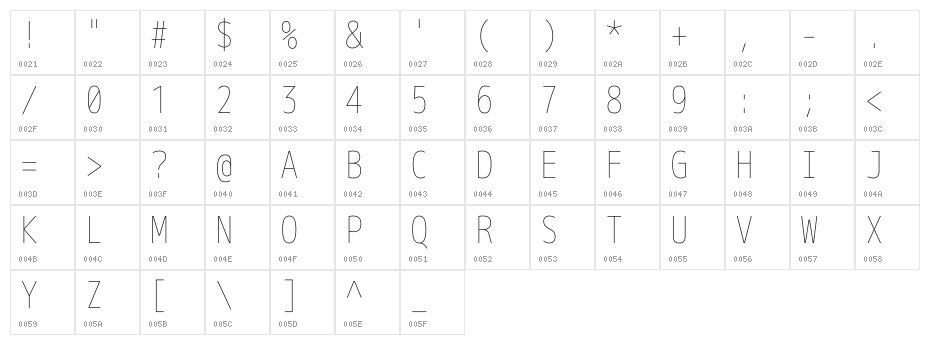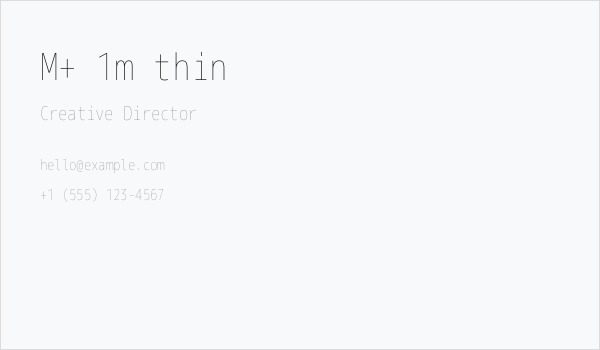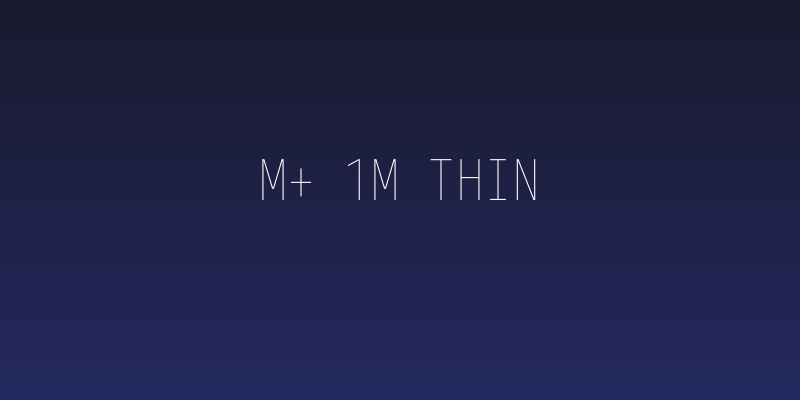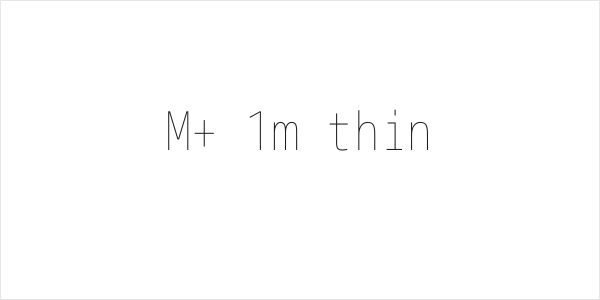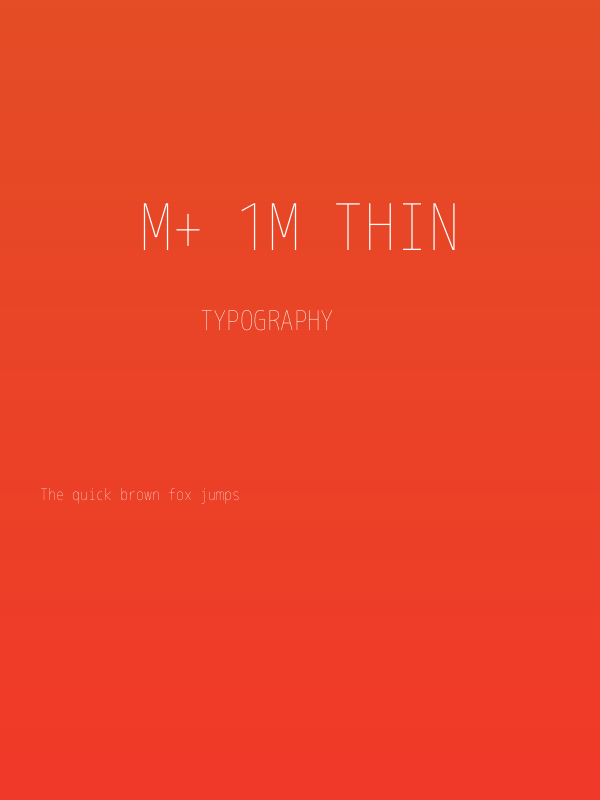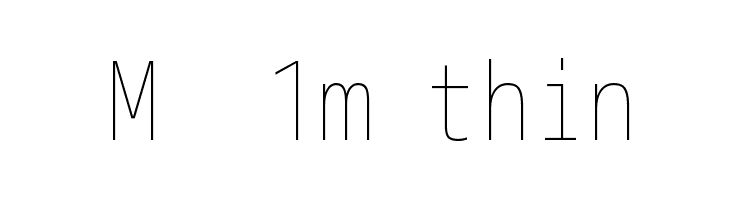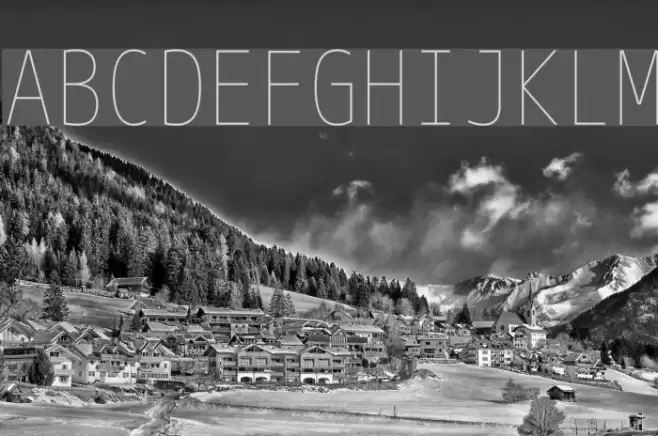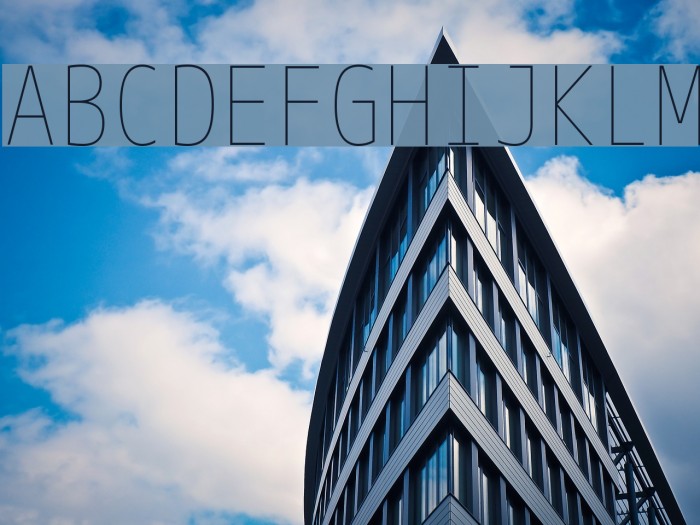
M+ 1m thin Font
| Anwendungsfall | Headlines, Body text, Logos |
| Vorgeschlagene Projekte | Ideal for modern branding, minimalist posters, sleek website headers, and elegant invitations. |